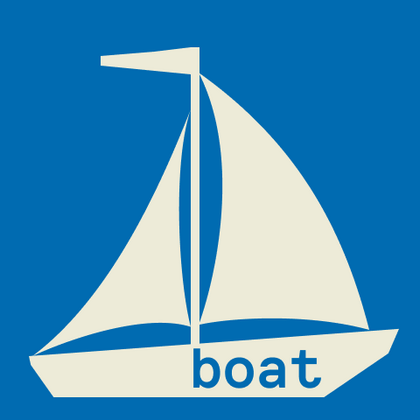
Шрифты для лодок (названий)
Эти специализированные гарнитуры созданы для нанесения на корпуса судов и морскую атрибутику. Шрифты для лодок устойчивы к деформации при криволинейной поверхности и отлично видны на расстоянии. В каталоге TypeType представлены как классические шрифты с «волнообразными» элементами, так и современные геометричные решения — все они сохраняют четкость при нанесении методом гравировки, окраски или виниловой аппликации.
TT Odellia — старостильная антиква с современным рисунком, вдохновлённая венецианскими шрифтами и классической музыкой.
TT Chocolates — изящный гуманистический гротеск сo сбалансированными пропорциями, близкими к классическим. Шрифт с приятным дружелюбным характером, который интуитивно воспринимается как что-то знакомое.
TT Nooks Script — шрифт с уникальным рисунком, который не имеет прямых аналогов.
TT Qurdisma — узкий и плотный декоративный шрифт, напоминающий причудливое растение. Вьющиеся, плавные контуры рождают растительный орнамент.
TT Dott — экспериментальный пиксельный гротеск, в котором за основу пикселя взят круг. Это пластичный и необычный акцидентный шрифт, вызывающий ассоциации одновременно с вышивкой и техно-вечеринками.
TT Commons™ Classic — универсальный геометрический гротеск для широкого круга задач.
TT Runs — это выразительный шрифт, который идеально впишется в проекты со спортивной тематикой. При этом гарнитура отлично подойдет и для других современных проектов: после обновления сфера ее применения значительно расширилась.
TT Severs — это геометрический гротеск с ярко выраженными элементами внутренних скруглений. Отличительной особенностью TT Severs является необычная форма внутренних овалов, которая отсылает нас к стилю традиционной арабской письменности.
TT Jenevers стилистически относится к голландским антиквам нового стиля. В гарнитуре присутствуют характерные детали, свойственные голландским антиквам — это ассиметричная форма засечек или нерегулярный наклон овалов.
TT Quaris — изысканная и современная ленточная антиква. Перед разработкой этой гарнитуры мы провели глубокое исследование архетипов ленточных антикв.
TT Bakers — пластичная антиква с нежным и живым характером. Этот шрифт похож на свежую выпечку: он тёплый и мягкий, особенно в жирных начертаниях.
TT Ricordi Greto — неконтрастный флорентийский гротеск с динамичными пропорциями. Это единственный гротеск среди антикв в коллекции TT Ricordi, при этом в нем сохранились едва заметные засечки, отсылающие к прототипу.
TT Marks — рукописный шрифт с динамичным ритмом, тёплым характером и слегка ностальгическим настроением. Он вдохновлён классическими американскими расписанными вывесками (sign painting), которые когда-то художники создавали вручную с помощью кистей и красок. Сегодня надписи в таком стиле снова набирают популярность.
TT Disruptors — дуктальный рукописный шрифт, созданный с помощью маркера. Его рисунок уникален: потёртости, неравномерная толщина штрихов и удлинённые выносные элементы придают ему живую, динамичную текстуру и ощущение рукотворности. Характер этого шрифта своенравный и эмоциональный, но при этом тёплый и душевный.
TT Gentlemens — динамичный рукописный шрифт, в котором серьёзность и чёткость письма сочетается с элегантностью и изысканностью. У него характер и стиль настоящего джентльмена: сдержанный и всегда уместный, но при этом уверенный и эффектный.
TT Ramillas — стильная и современная антиква. Включает уникальные декоративные начертания и буквицы с цветочным орнаментом.
TT Gertika — геометрический гротеск с динамичным характером и танцующим ритмом. Идея шрифта зародилась из леттеринга на американском плакате второй половины 30-х годов.